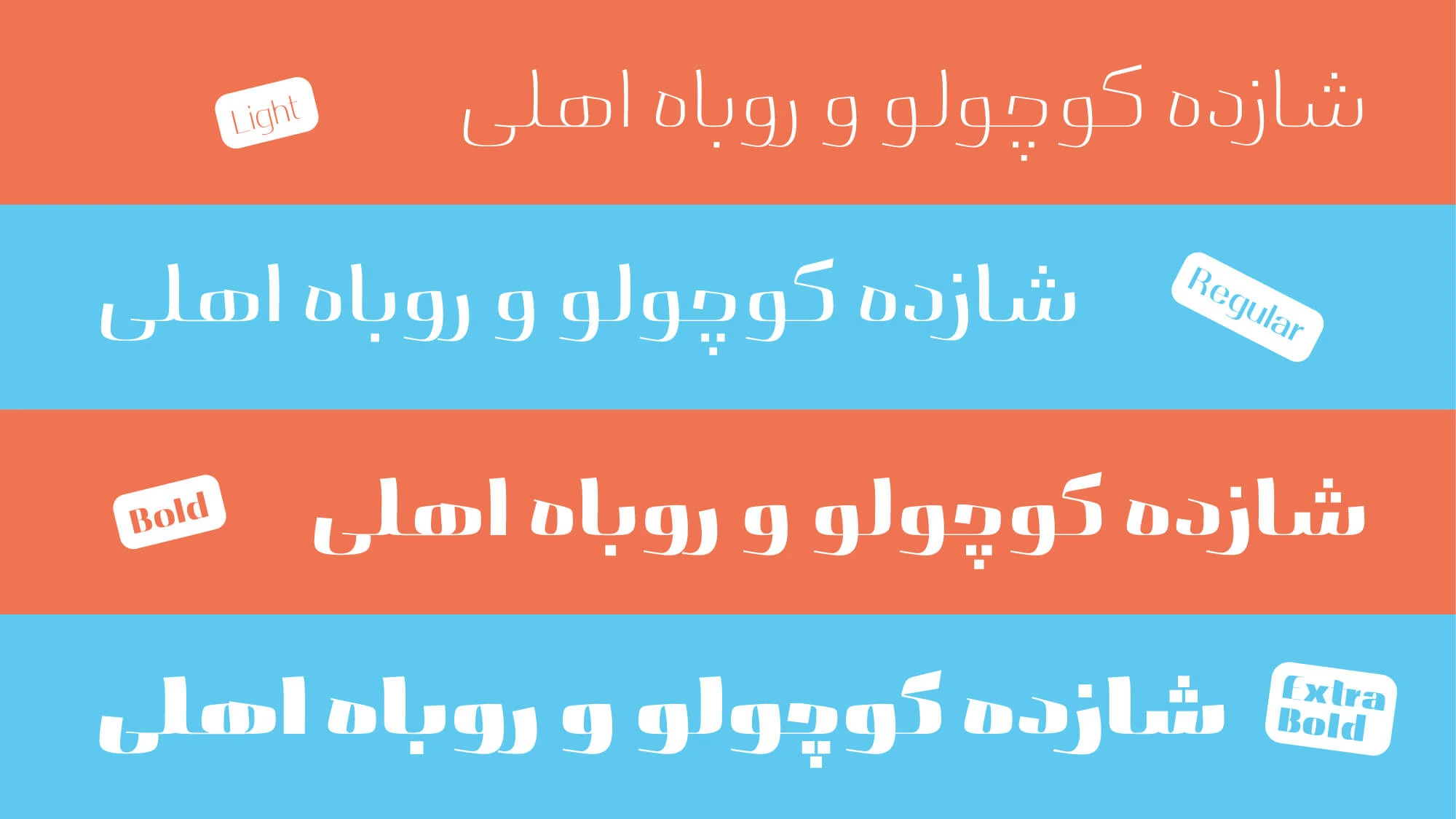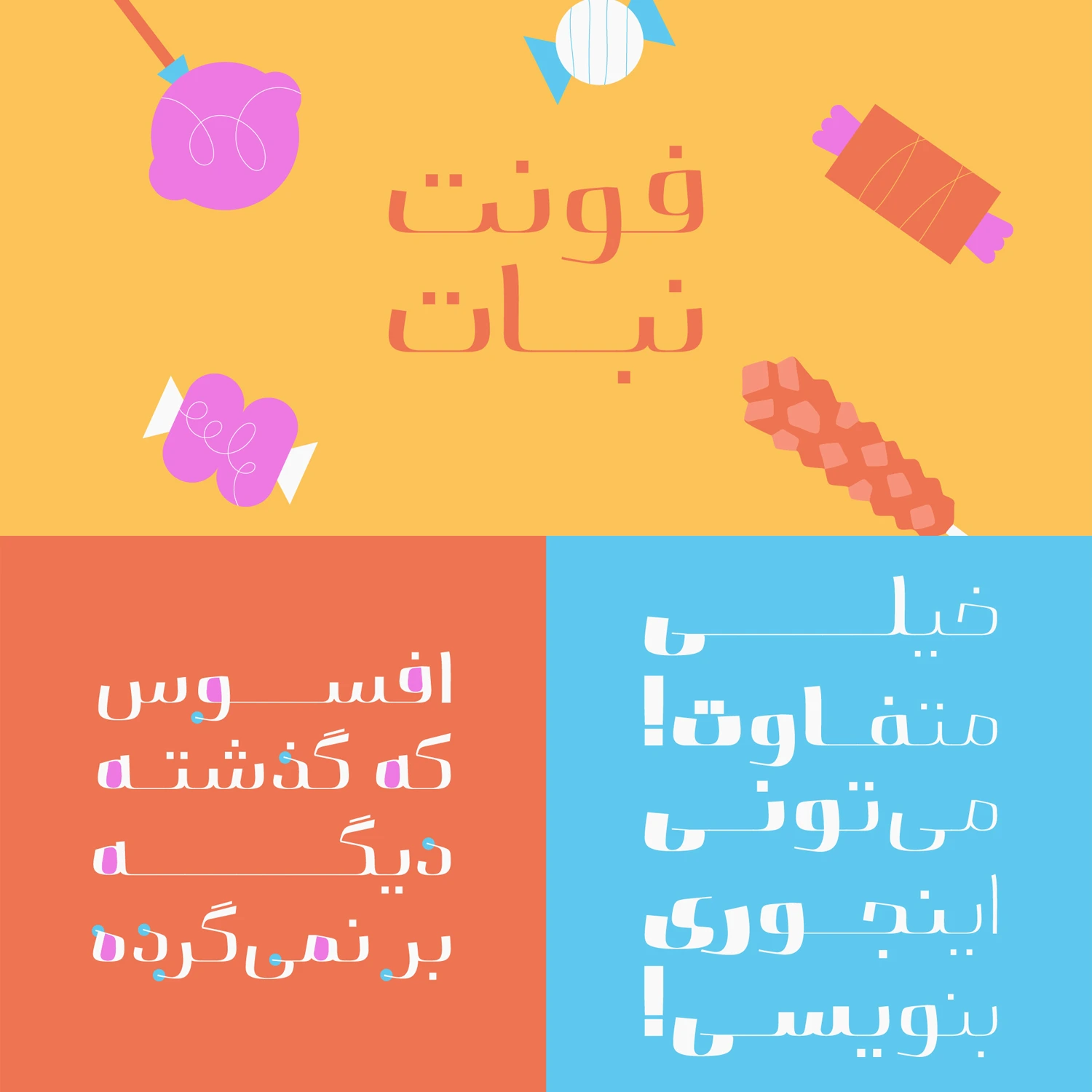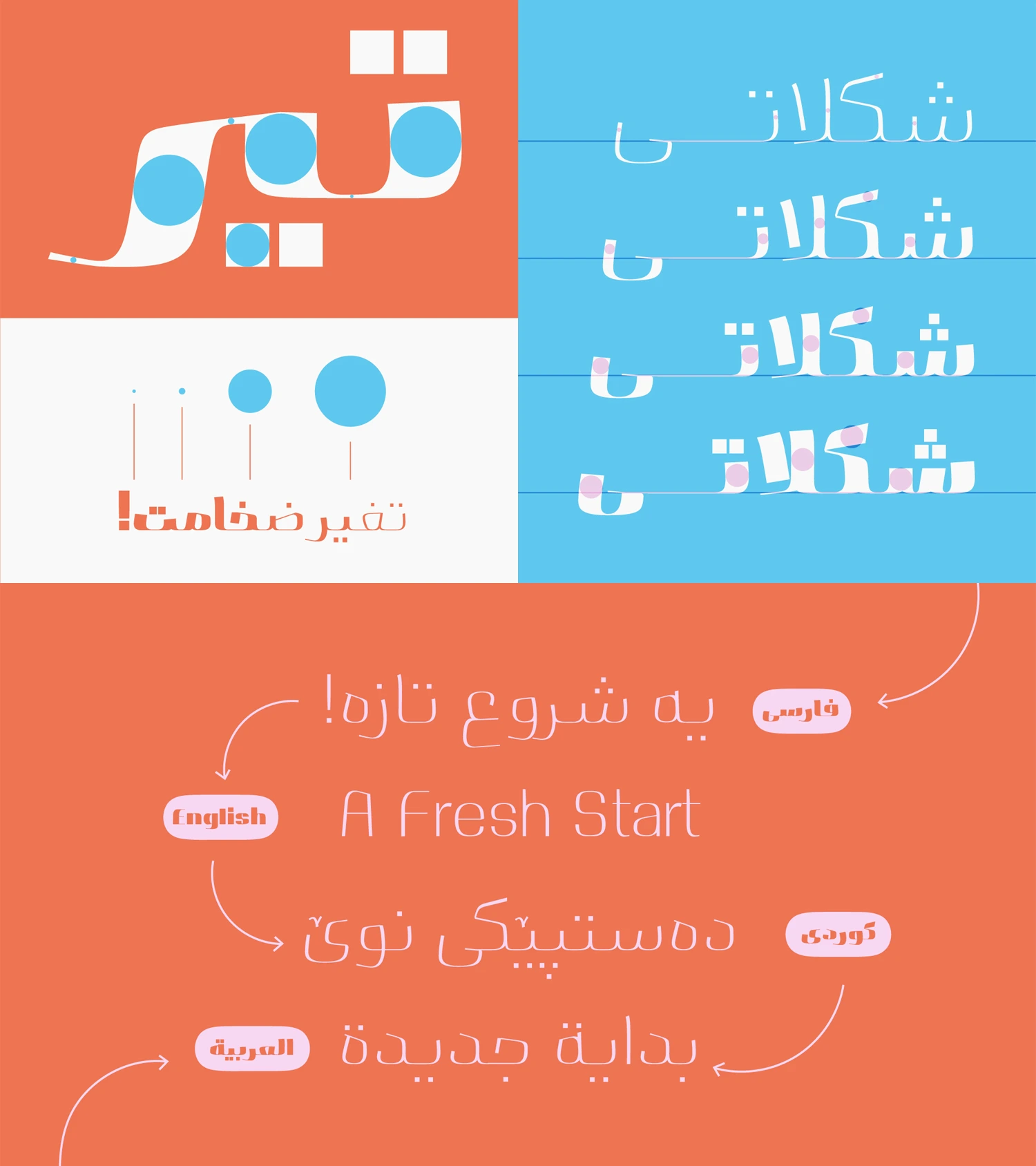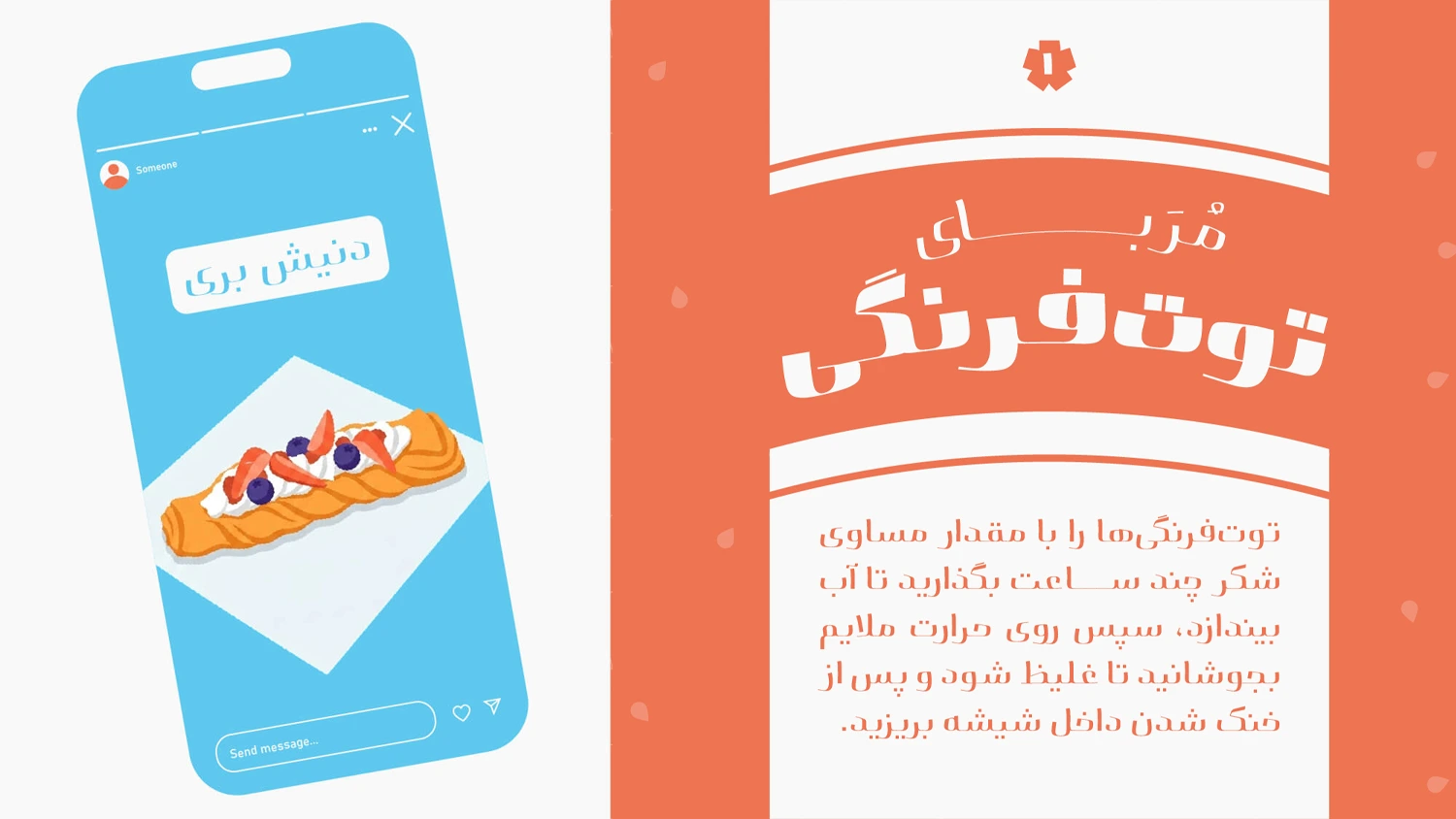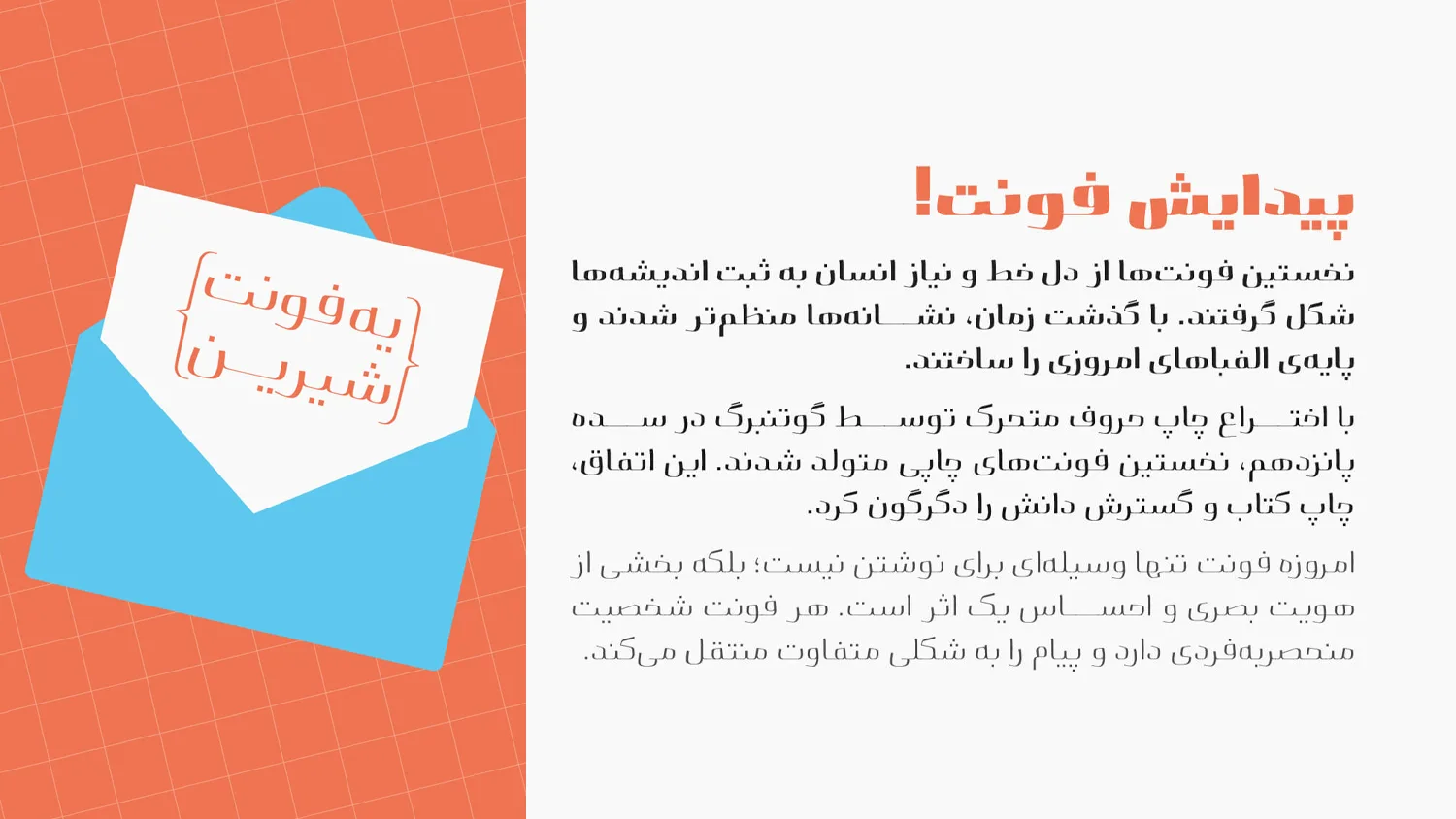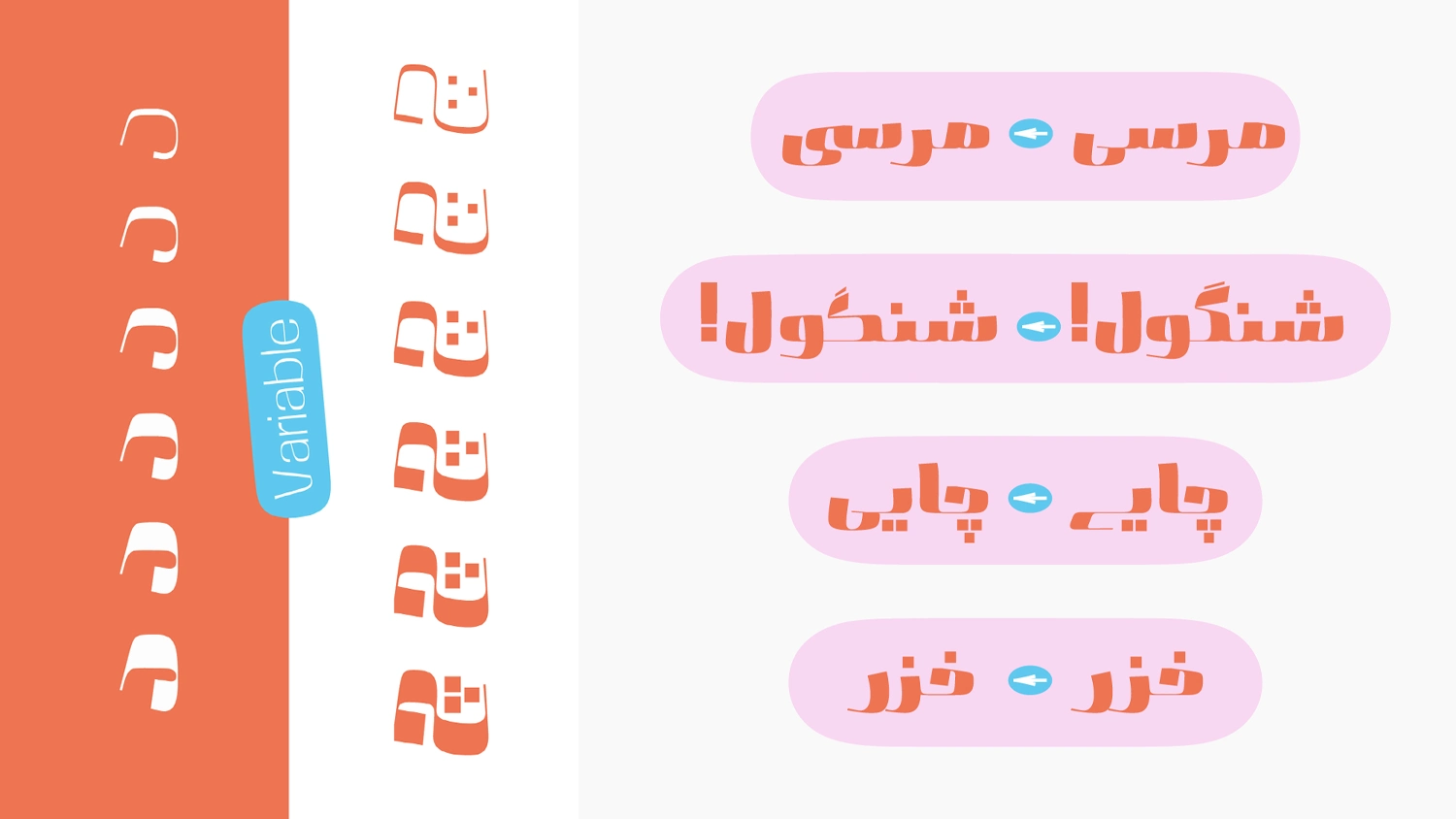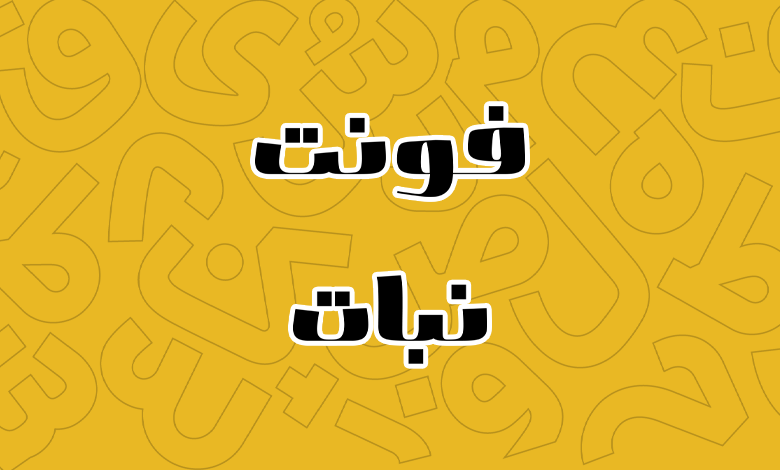
فونت نبات (Nabat)
فونت نبات (به انگلیسی: Nabat) قلمی با ساختار هندسی و فانتزی است که در طراحی آن از ترکیب دو ساختار خطوط عمودی پهن و خطوط افقی نازک استفاده شده است. فونتی پویا و مناسب عناوین و تبلیغات است که با شخصیت بازیگوش خود، حسابی جلب توجه میکند.
محمدحسین فربخش این فونت را به شکلی طراحی کرده که با گسترش عرض حروف وزن گرفته و خود را بهتر نشان میدهند. ساختار فونت بر اساس حروف لاتین طراحی شده است. این قلم با همکاری امیر مصباحی به فونت تبدیل شده است.
فونت نبات TTF شامل ۴ وزن Light، Regular، Bold و Extra Bold است. از زبانهای فارسی، انگلیسی، عربی و کوردی پشتیبانی میکند. دارای نسخه وریبل با متغیر تغییر وزن است که بدون نیاز به نصب ۴ فونت مختلف، میتوانید فقط با نصب یک فایل فونت از همه وزنها استفاده کنید.
یکی از نکات مثبت این فونت به ایده ساخت آن مربوط میشود که باعث شده حروف انگلیسی در کنار حروف فارسی، عربی و کوردی که رسمخط کاملا متفاوتی دارند، ساختاری یکپارچه داشته باشند. از اینرو در متنهای چندزبانه، شاهد یکپارچگی هستیم.
دیگر ویژگی این فونت پشتیبانی از حروف جایگزین و لیگچرهاست که با استفاده از تنظیمات OpenType میتوانید از آنها استفاده کنید. این ساختارها کمک میکنند تا بتوانید کلمات را به شکلهای مختلفی تایپ کنید تا برخی حروف ساختاری متفاوت داشته باشند. چنین قابلیتی برای فونتهای عناوین و بهویژه تبلیغات یک مزیت عالی است.
اگر در پروژههای طراحی خود نیاز به فونتی پویا، صمیمی، یکپارچه برای زبانهای مختلف و پرانرژی نیاز دارید، فونت نبات مناسب کار شماست. طراحی بستهبندی محصولات، عناوین مجلات و کتابها یا تبلیغات محیطی به صورت بنر از دیگر کاربردهای این قلم است.